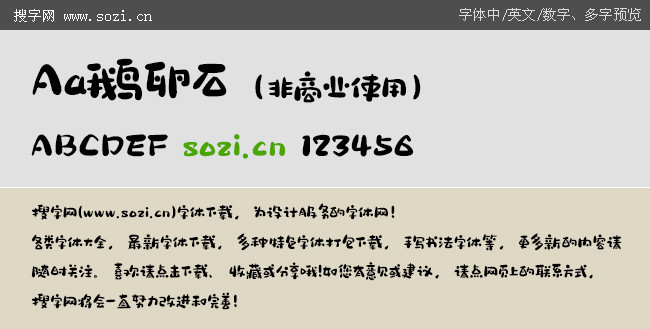
Aa鵝卵石
搜字網(wǎng)給大家提供一款A(yù)a鵝卵石(非商業(yè)使用)中文字體下載,該字體是一款卡通中文字體,字體靈活多變,字形天真可愛,童趣十足,適合兒童書裝設(shè)計、兒童包裝、海報設(shè)計等應(yīng)用(此字體為個人非商用版,商用可以聯(lián)系QQ:1006760504)。